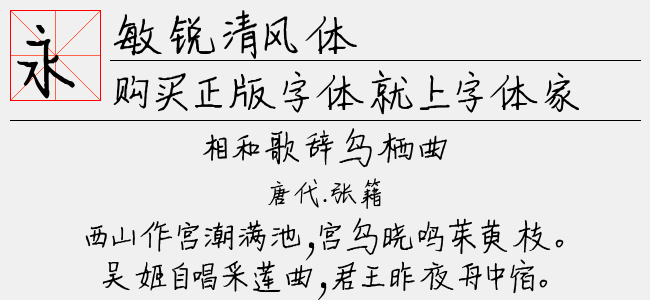
敏锐清风体是一款大小4.40 M的敏锐字库字体,主要特征是手写,手书风格,行书,钢笔,,敏锐清风体为TTF格式的文件,采用安装嵌入,包含了英文、拉丁文以及日文等符号,字宽,当前版本是Version 1.000,共计6763个汉字及26个英文大小写字母。
字体作者:敏锐字库
字体名称:敏锐清风体
字体内容:6763个汉字及26个英文大小写字母
字体家族:敏锐字库